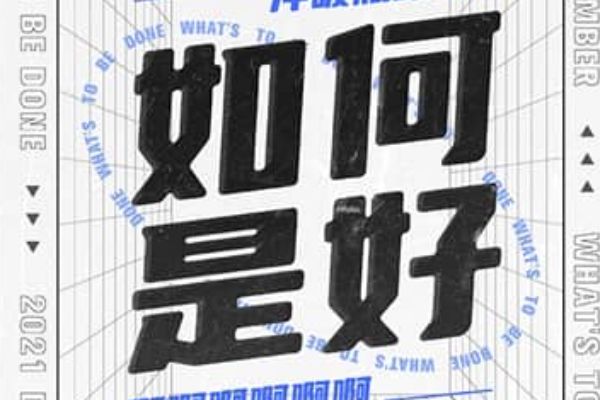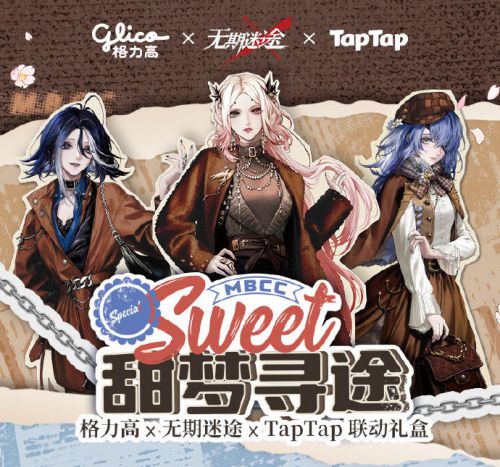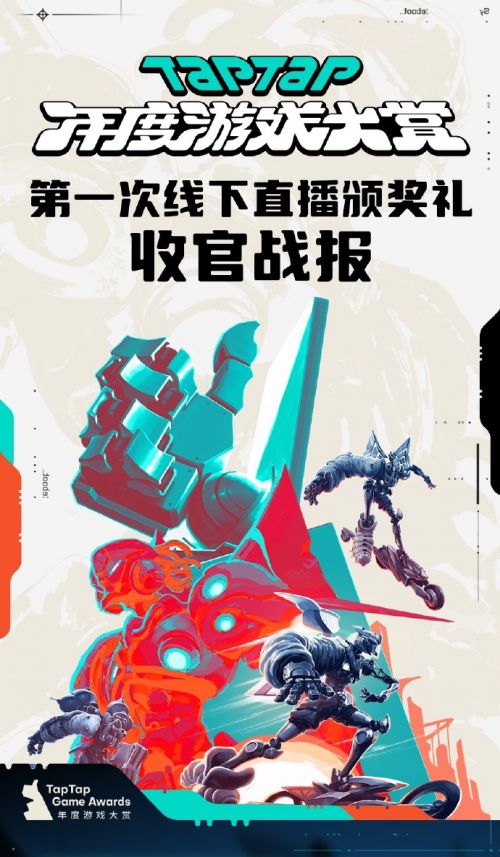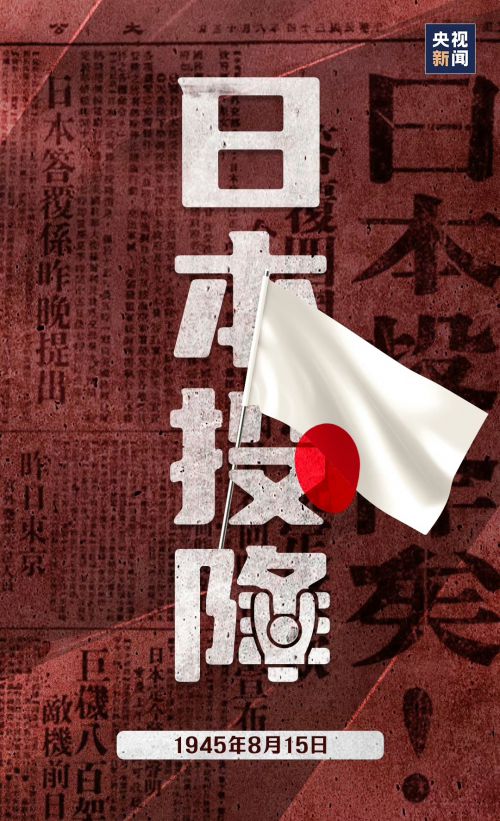
优设标题圆
优设标题圆是一款风格有趣的创意字体,以独特的设计巧思成为标题场景的亮眼之选。字体字形方正稳重,重心居中的结构搭配宽博的中宫,让文字在视觉上舒展大气,既保留了标题所需的端庄感,又通过灵动细节打破沉闷。 优设标题圆在笔型设计上充满亲和力:整体采用柔和圆角处理,搭配圆润的笔画端头,弱化了传统粗体的锐利边缘,增添了萌趣活泼的视觉气质;笔画连接处的断开设计,则为字体注入呼吸感,避免密集排列时的视觉拥挤,让文字层次更分明。字重饱满的粗体设定与均匀的笔画粗细,进一步强化了标题的醒目度,即使在小尺寸显示下也能保持清晰张力。 作为免费商用字体,优设标题圆适用于广告海报、社交媒体头图、电商Banner等多元场景,无论是活泼的品牌宣传还是创意活动标题,都能轻松驾驭,助力创作者打造吸睛又合规的设计作品。